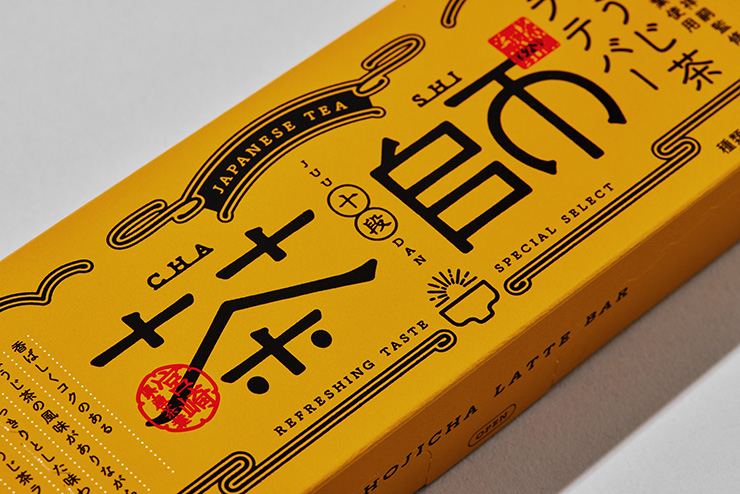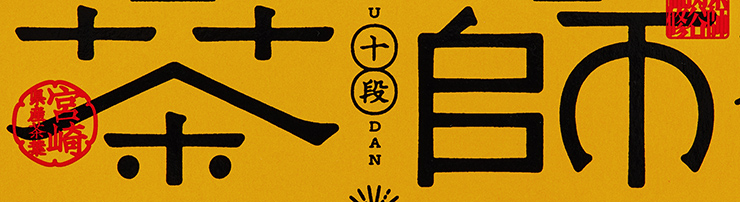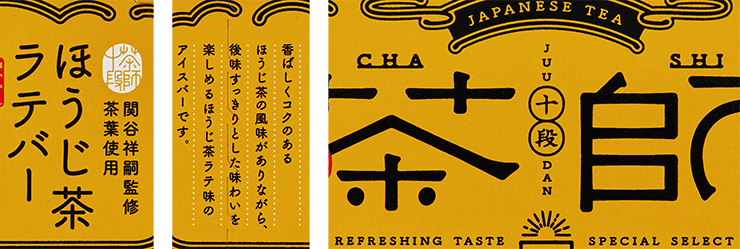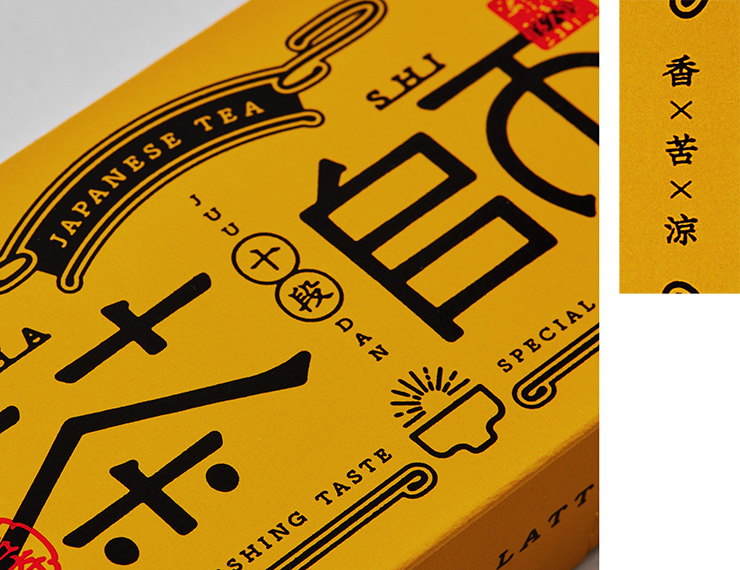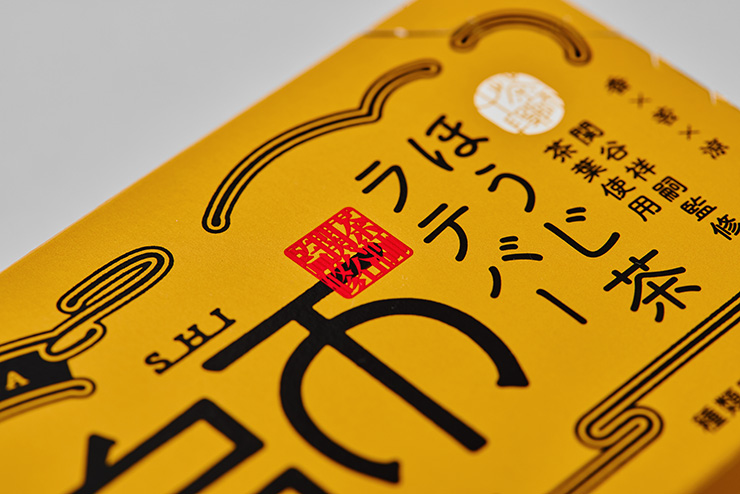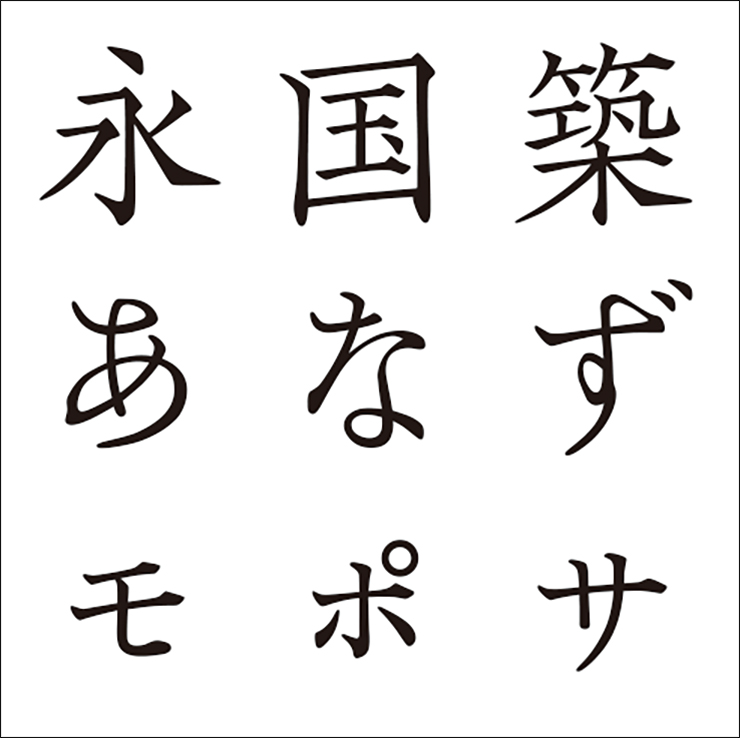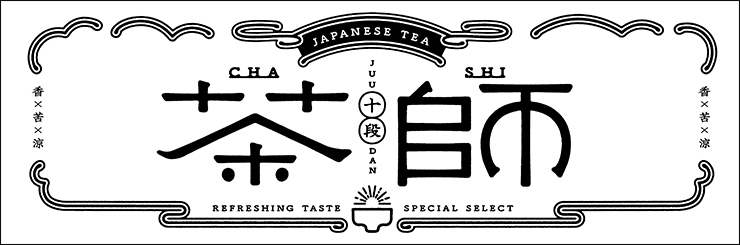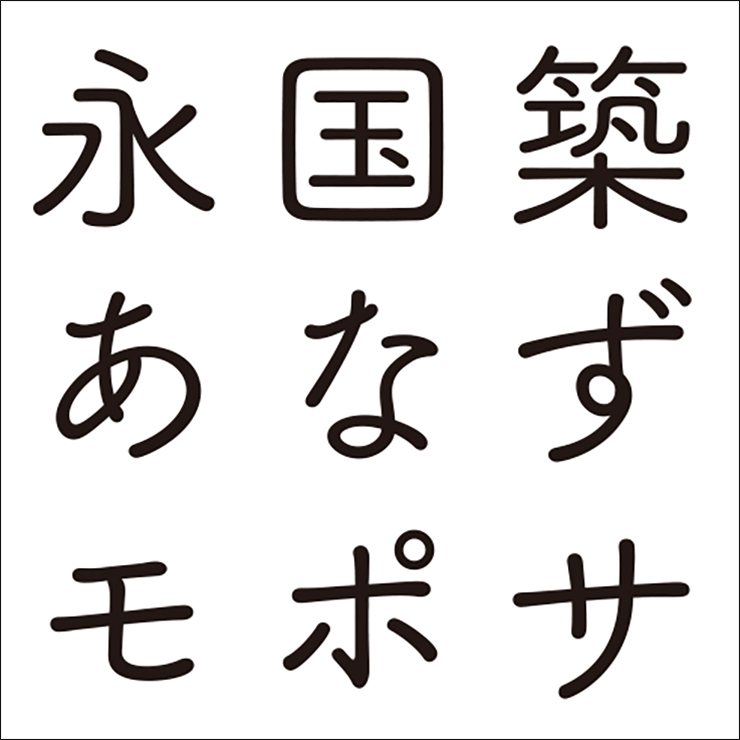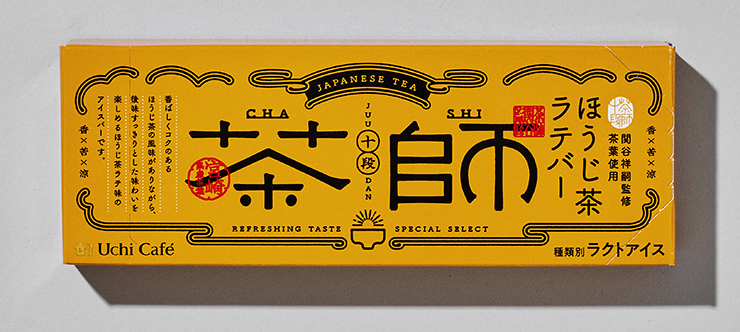
今回は、ローソンのスイーツブランド「ウチカフェ」の商品『ウチカフェ 茶師十段関谷祥嗣監修茶葉使用 ほうじ茶ラテバー』のパッケージの使用フォントについて、デザインを手がけたKnot for, Inc.に取材。趣がありつつモダンで印象的なタイトル文字などの制作過程に迫ります。
緩急のあるデザインでカジュアルかつ明るいトーンを出す
全国でも十数人しかいない“茶師十段”の関谷祥嗣氏が厳選した、薫り高い宮崎県産茶葉の豊かで華やかな風味を堪能できるアイス『ウチカフェ 茶師十段関谷祥嗣監修茶葉使用 ほうじ茶ラテバー』。シリーズ化されており、「ほうじ茶」のほかにも「抹茶」と「和紅茶」がラインアップされている。
パッケージでは、お茶の良し悪しを見極める目利きである「茶師」にフォーカスしながらも、お茶から連想する格式高い和のイメージをあえて避け、明るくカジュアルなトーンが追求された。アートディレクターの上杉滝さんによれば「パッケージの最重要テーマである『茶師』を大きくレイアウトしてアイキャッチとしました。ターゲットが幅広い商品ですので、若年層にも受け入れられやすいカジュアルなイメージにすべく、『茶師』の文字は緩く明るいスキのある印象を目指して調整を重ねています。文字要素の周囲を飾るオーナメントは、お茶の湯気がモチーフになっています」とのことだ。
Font.01「オリジナル」
カジュアルで明るくスキのある表情の文字に
商品名のうち「茶師」部分は、商品の幅広いターゲットに合わせて作り起こされたオリジナルの文字。お茶の伝統的なイメージはあえて避け、カジュアルなテイストで制作された。図はその制作途中のもの。
上杉さんによれば「お茶というと、伝統的で格式の高い佇まいを思い浮かべますが、今回は若年層にも受け入れられるようなトーンを目指し、カジュアルで明るくスキのある表情になるよう心がけました。『茶師』の文字はいちばんに目に留まる部分なので、作り起こしたあとで輪郭ににじみやムラのような表情を与え、懐かしさや優しいニュアンスが少し出るように調整しています」とのことだ。
Font.02「かもめ龍爪」
宋朝体で軽くニュートラルな印象に
商品名の「十段」部分と、キャッチコピー「香×苦×涼」は、細く鋭いはらいが特徴的な宋朝体「かもめ龍爪」(モリサワ)に。そのシャープな印象がコンセプトに合っていたため選択された。上杉さんによれば「メインの『茶師』を引き立たせるのが今回のデザインのテーマでした。そのため、ほかの文字要素はできるだけ軽いニュートラルな印象になるよう心がけています」とのことだ。
Font.03「筑紫B丸ゴシック」
温かみのある丸ゴシック体を選択
商品名のうち「ほうじ茶ラテバー」や「関谷祥嗣監修茶葉使用」部分、ボディコピー、欧文部分は、すべて「筑紫B丸ゴシック」(フォントワークス)がベースに。メインの「茶師」部分を引き立たせるため、軽やかでニュートラルな印象の書体が選択された。ウェイトは「ほうじ茶ラテバー」が「M」、「関谷祥嗣監修茶葉使用」やボディコピー「香ばしくコクのある~」部分が「E」などとなっている。
上杉さんによれば「メインの『茶師』はにじみなどの加工を施して揺らぎのある表情にしていますが、それ以外の文字要素は若干太らせている箇所が部分的にある程度で、基本的に加工はしていません。ディテールを詰める部分と詰めない部分の対比がカジュアルさを生み、画面に緩急が生まれればと考えてデザインしています」とのこと。